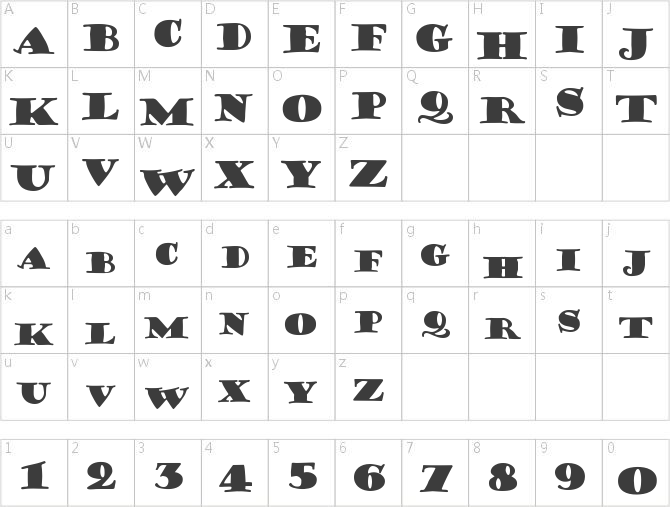
FZ-JAZZY-38
FZ-JAZZY-38字體字庫(kù)是一款讓人賞心悅目、百看不厭的英文字體,適合各類(lèi)廣告和產(chǎn)品包裝設(shè)計(jì)應(yīng)用,字體大小0.06MB,格式為ttf字體,上傳用戶是 造物設(shè)計(jì)師,作者/版權(quán)方為未知